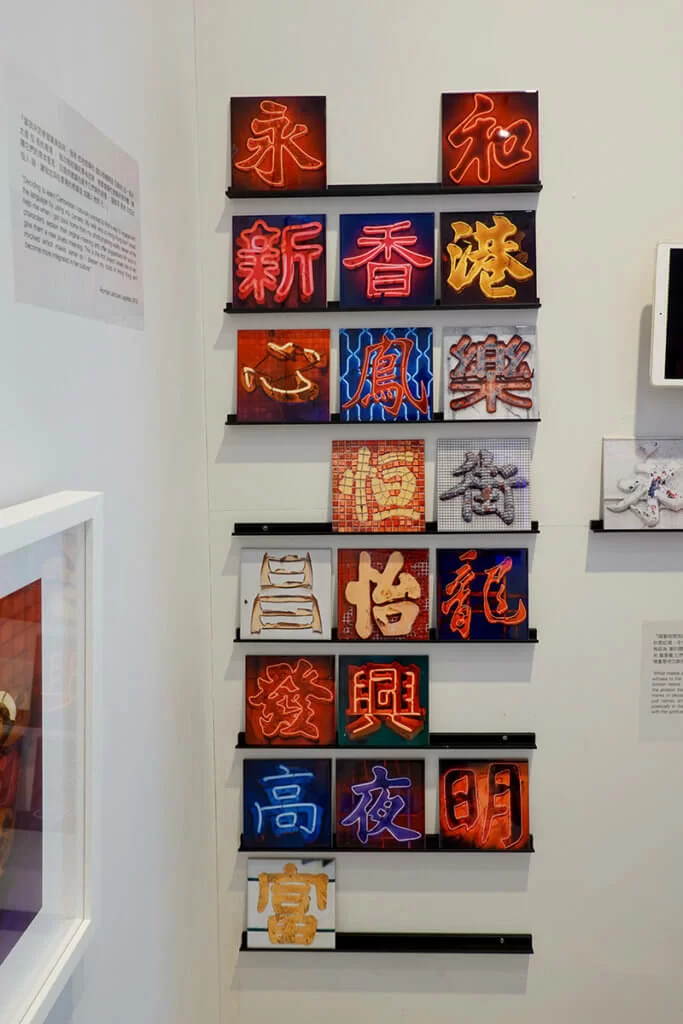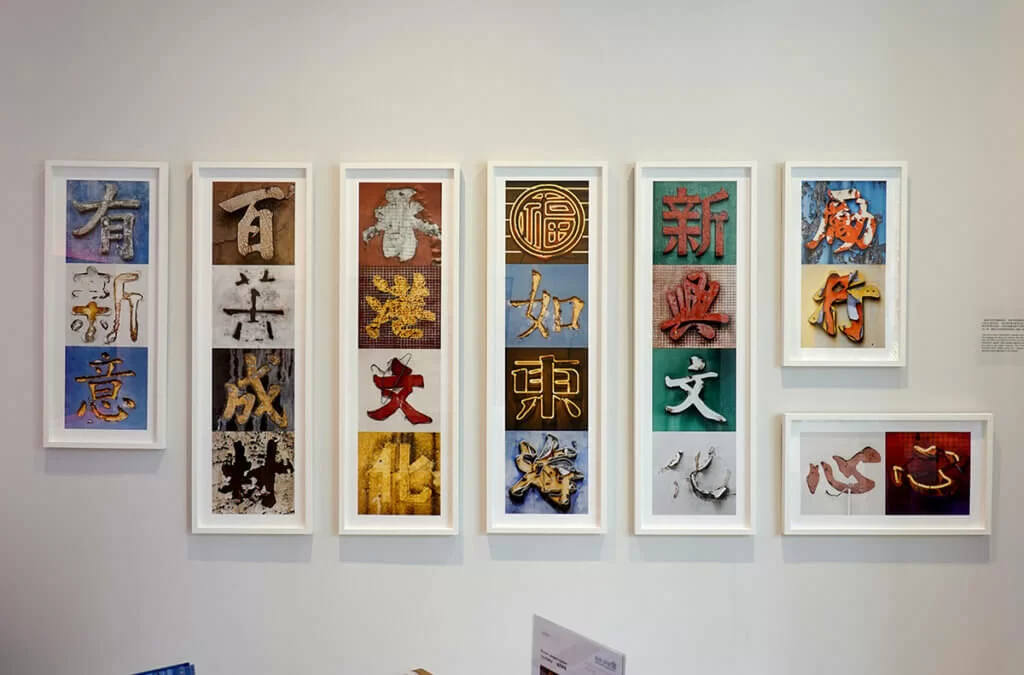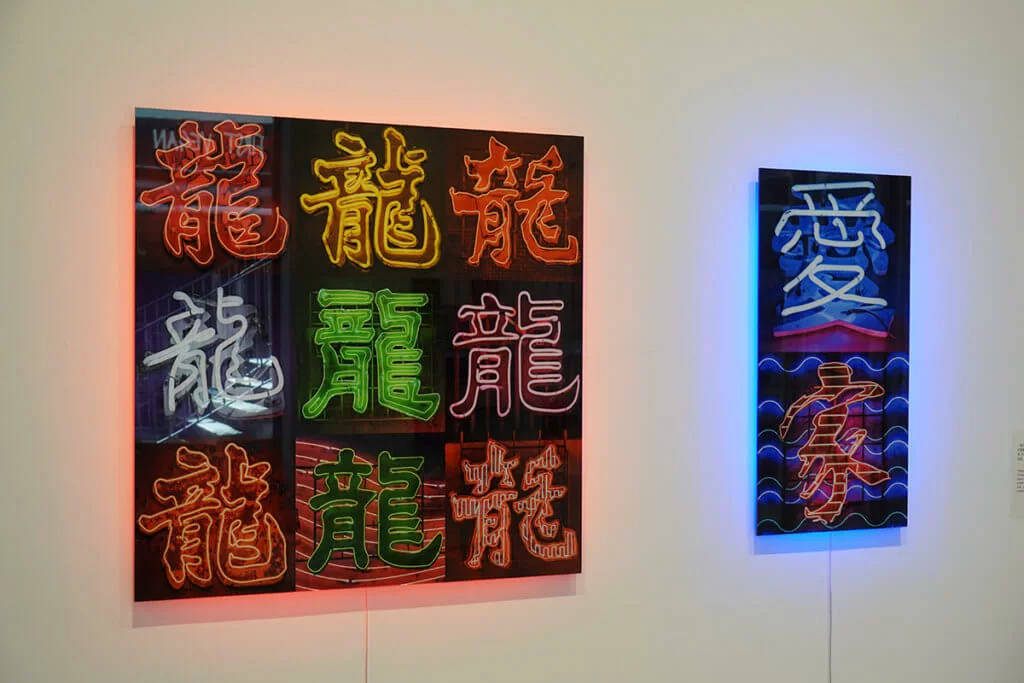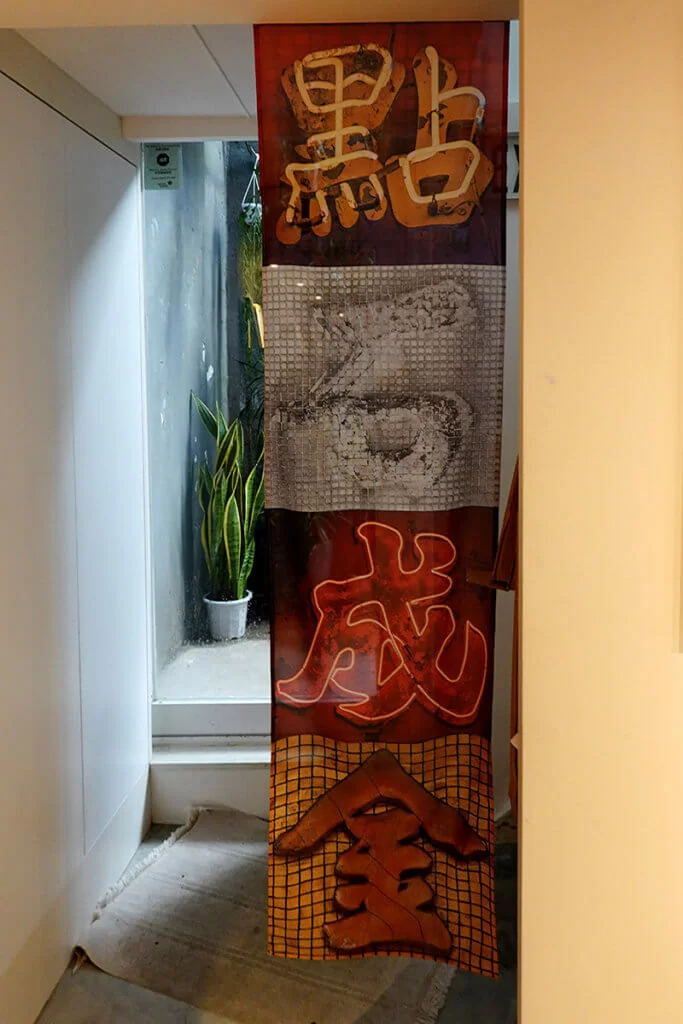
聽過有一種說法,「熟地無風景」。意思是最熟悉的地方,縱有各種美景,亦會習以為常,視而不見。正如香港街道上的招牌,外國人看見無不讚嘆不已。可是近年政府對招牌的規管非常嚴格,屋宇署根據《建築物條例》不斷清拆,昔日令港人引以自豪的風景,已被破壞得七零八落。這引起了我們對傳統招牌及手寫字體的重視,並開始搶救式的記錄及研究,於是香港人眼中的「爛鬼招牌」,漸漸變成本地藝術的一部分,登上大雅之堂。
法國攝影師Romain Jacquet-Lagrèze拍下香港招牌字, 並組成不同的語句。拍攝對象有完整招牌字,也有較 破舊的,當中有個「文」字還鈎住了一個衣架。
法國攝影師Romain Jacquet-Lagrèze拍下香港招牌字, 並組成不同的語句。拍攝對象有完整招牌字,也有較破舊的,當中有個「文」字還鈎住了一個衣架。
作為一個對藝術「識條鐵」的招牌佬,我有幸參觀了由法籍攝影師Romain Jacquet Lagrèze企劃的《城市詩意》展覽。展場不大,一邊展出以城市植物為主題的《石林獨秀》系列照片,拍攝香港石屎森林內的點點翠綠。不過令我最有興趣的,還是以招牌為主題的照片,他拍下不同的香港招牌字,再拼湊成有意思的句語。這種表現手法我以前也見過,但細看之下,不得不佩服攝影師的細密心思。
除了攝影師Romain的個人觀察,他的香港籍太太也給予了相當大的幫助,替他解釋街道上的文字內容,並協助他選取題材。這種中外合璧的視角,豐富了作品的內涵。
瓷磚上印有各式招牌字
在妻子協助下,攝影師拍下不同的香港招牌字,再拼湊成有意思的句語。
破爛招牌蘊藏工藝秘密
我曾做一些小規模的香港招牌調查和研究,其中一項心得是:欣賞招牌,要找手工精美、保存完好的;研究招牌,要找手工稍次或者破爛的。招牌之美,往往取決於工匠高超的製作技巧,唯有透過招牌的瑕疵及破損,方能窺探隱藏其中的秘密。
在這個展覽中,攝影師除了走遍大街小巷,察看各種物料製作的招牌外,還能夠欣賞各種狀況的新舊招牌,將破爛的招牌變成藝術養分,轉化成作品的材料。他說:「我認為日漸的磨損,反而將它們轉化為更深層次的事物。」
作品上展示的舊招牌,可能就是日常街坊或商戶欲除之而後快的破爛招牌:字身半邊鬆脫,歪斜地卡住了一個衣架;字面油漆老化龜裂;脫色變形,剝離牆身的膠貼字;甚至是完全脫落,僅剩下留在牆上的歲月痕迹等。原來將其集合起來,就是一幅值得欣賞的圖畫,只是我們平日沒有留意吧。
霓虹燈「龍」結構各異
除了舊招牌,出現頻率最高的一定是霓虹招牌。它是最能代表香港的事物之一,可惜同樣正經歷瘋狂的清拆,亟需珍視及保育。攝 影師將九張霓虹燈「龍」字相片合併成「九宮格」,當中包含紅黃白綠四種顏色,也有不同大小結構的霓虹招牌。
細看這幅霓虹燈「龍」字九宮格,就能發現即使是同 一個字,也有不同製作方式。
細看這幅霓虹燈「龍」字九宮格,就能發現即使是同一個字,也有不同製作方式。
其中左豎行中間的是「單鈎字」,即以單線描畫字形,屬於較小的招牌字;頂行三字、右豎行中間及左下角同屬於「雙鈎字」,以霓虹管勾劃字的輪廊,屬中等大小招牌;正中央的龍字則屬「雙鈎加中線」;右下是「雙鈎加 平行線」,兩者均屬較大的字。這些細節,招牌業內人士當然可輕易看到,這也突顯了攝影師細緻的觀察力。
展覽中的作品相當值得欣賞。如果要給意見的話,或者可以再展出多一點的作品吧。此外,場內的中文解說有相當多的缺字漏字, 或許是印刷輸出時的失誤,要改善的話應該不難。
瓷磚上印有各式招牌字